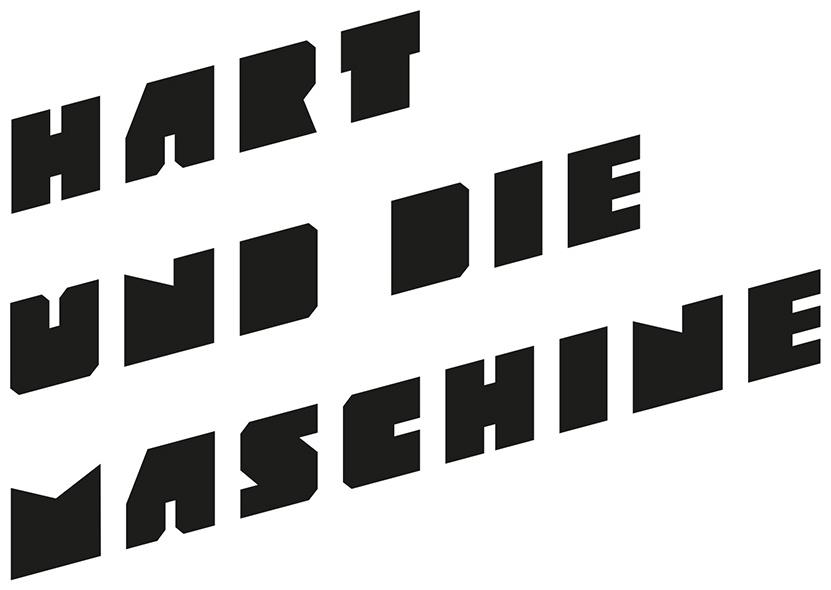
Sehr fette Block-Schrift: Identifikation oder annähernder Font?
ich habe hier ein Logo aus einem Design, was ich mit den üblichen Mitteln nicht identifizieren kann. In einem PDF verbarg es sich als Pfade, weswegen ich zuerst von einer eigenen Handzeichnung ausgehen muss. Aber wer weiß, vielleicht gibt es doch diesen blockigen superfetten Font und er wurde nur schräggestellt. Wenn der Font nicht identifiziert werden kann, wäre ich um Alternativvorschläge für ähnliche eckige, sehr fette Fonts dankbar.
Hier erst mal mein Fundstück:
Gelöst von Jens Pielawa
Eine Prisma Black mit weißer Outline, um die Zwischenräume zu vergrößern.
Ich hab's mittlerweile gefunden: es ist die MOD von Fontfabric:
Wahrscheinlich auch hier mit einer weißen Kontur etwas entschlankt und dann schräg gestellt.